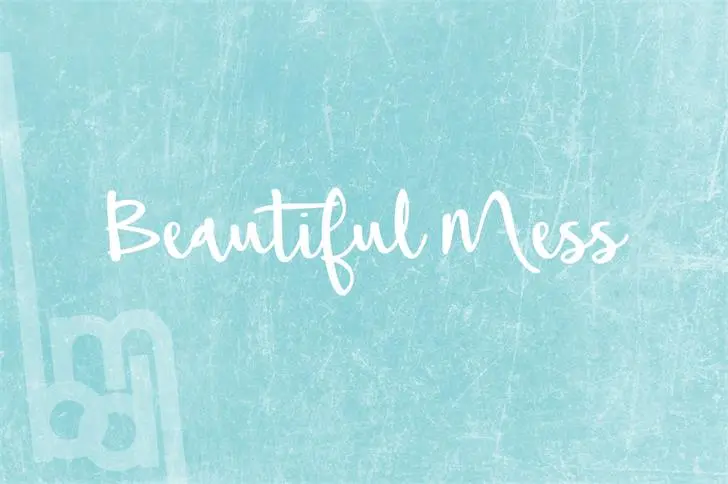
Beautiful Mess Font – Fonte Grátis
Beautiful Mess Font
A fonte Beautiful Mess é uma conexão script curiosa e ligeiramente desorganizada, perfeita para aqueles que buscam algo mais além do padrão convencional na tipografia. Com seu conjunto de caracteres latinos e latino-estendido, ela adiciona um toque casual e descontraído a qualquer projeto gráfico. Brittney Murphy Design criou esta fonte conectada com uma leve dose de charme pessoal, fazendo-a perfeitamente adequada para designs que valorizam originalidade sem perder o equilíbrio estético. Essa fonte é ideal tanto para textos em tamanho grande quanto em detalhes menores, proporcionando um toque único e aconchegante aos seus projetos digitais. Se você está buscando algo mais criativo na sua tipografia, Beautiful Mess pode ser o seu próximo design de fonte.